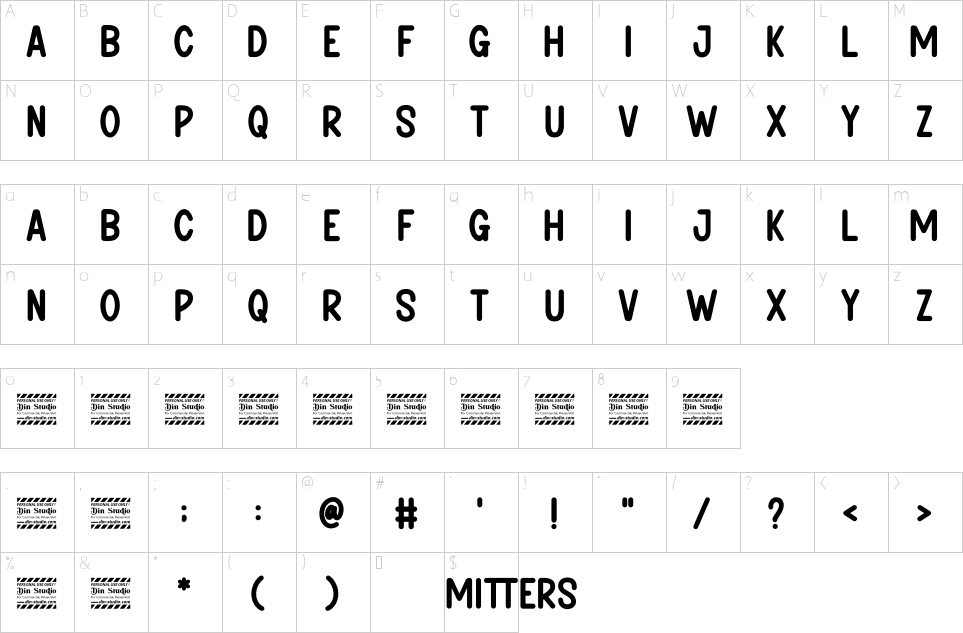
Descubra a fonte Mitters gratuita e elegante para Windows e Mac. Desenvolvida pelo Din Studio, Mitters foi um grande sucesso, com mais de quatro mil downloads. Suas linhas arredondadas e elegantes tornam Mitters perfeita para usar em materiais gráficos como logotipos, editoriais e materiais de marketing. Seja para usar em aplicativos de desktop ou para projetos online, a Mitters é uma opção versátil e gratuita. Não deixe de baixar e experimentar esta fonte moderna e atraente.